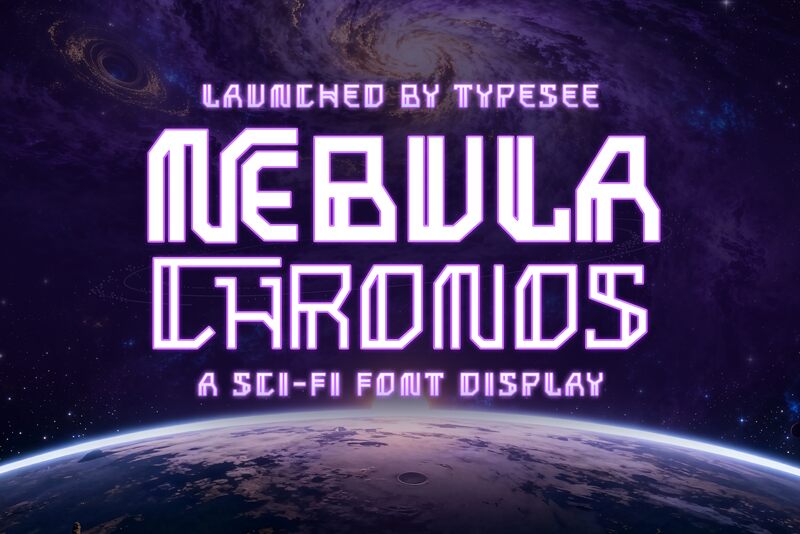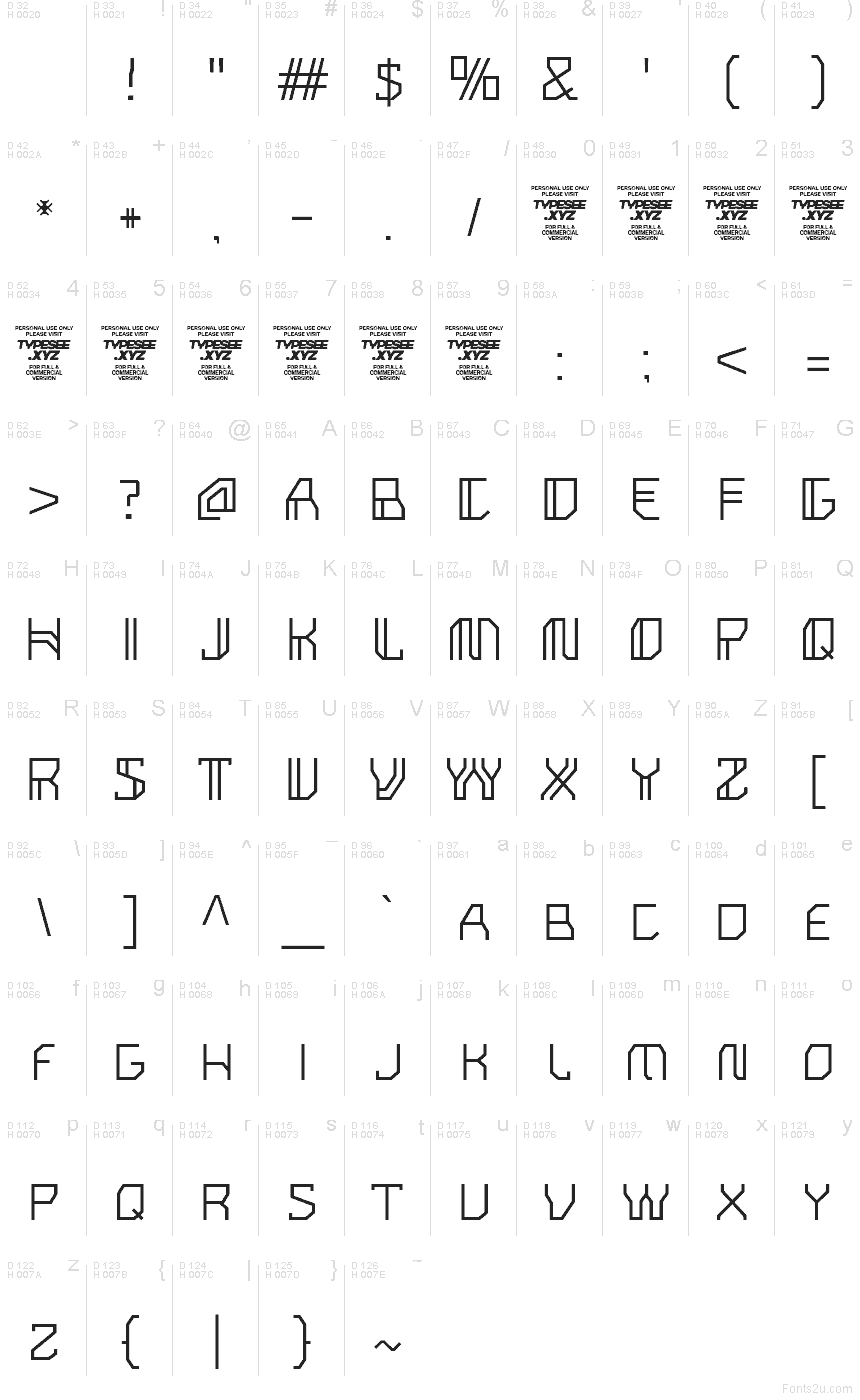
Nebula Chronos Light
Шрифт Nebula Chronos Light от Typesee Type Foundry — это футуристический акцидентный шрифт с резкими геометрическими формами и узкой, «вырезанной» структурой. Рисунок букв основан на прямых штрихах, угловатых соединениях и квадратных просветах, что придает алфавиту техничный ритм эпохи космических технологий без лишних украшений.
Nebula Chronos Light отлично подходит для научно-фантастических заголовков, игрового брендинга, постеров, баннеров технологических мероприятий, обложек альбомов и логотипов, где требуется структурная акцидентная гарнитура. Угловатая конструкция и открытые внутренние формы придают макетам точный, инженерный характер, идеально подходящий для смелых заголовков и коротких рекламных строк.